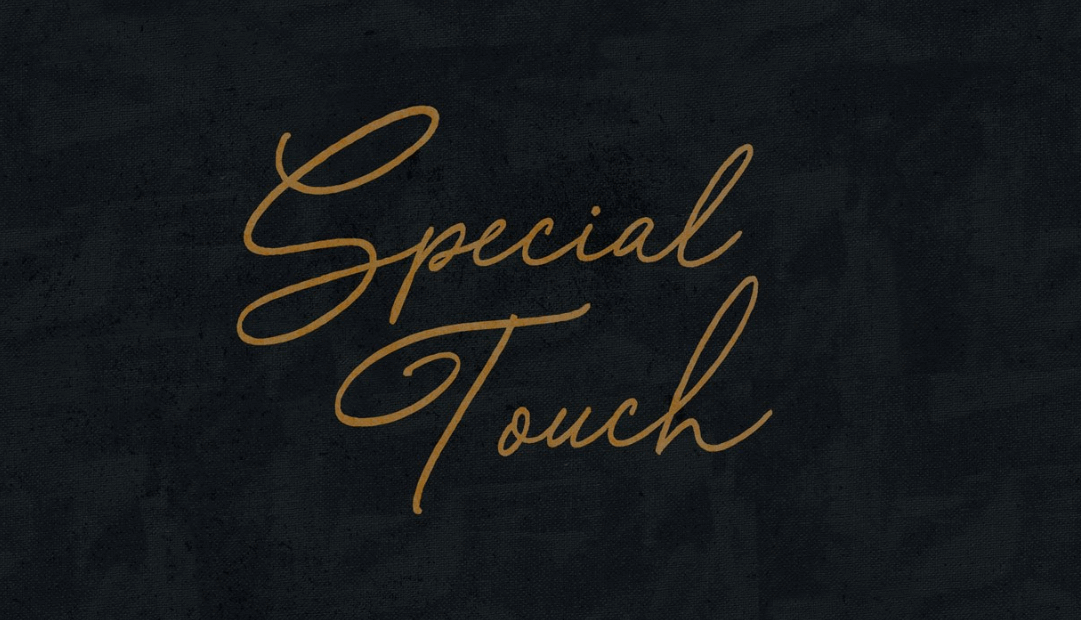
A Special Touch Script Font é uma criação meticulosa do Designer 178-MC, perfeitamente adaptada para diversos usos no design visual. Introduzida como uma nova opção entre as Brush Fonts, a fonte “Special Touch” oferece um toque único e sofisticado ideal para estilos de design criativos. Seu charme se destaca em papéis de cartão decorativos de Natal, convites de casamento, marca personalizada, identidade visual, design de blog ou qualquer outro projeto de design que valorize um estilo elegante e autêntico. Com uma fidelidade impressionante à fonte original, “Special Touch” também é perfeita para customização em arte impressa, selos e gravuras. Suas linhas sutis e seus traços elaborados criam uma sensação de profundidade que se adequa a diversos estilos de design moderno e minimalista. Este fonte certamente adicionará um toque especial aos projetos que buscam expressar elegância e sofisticação, tornando cada projeto personalizado ainda mais único e único.